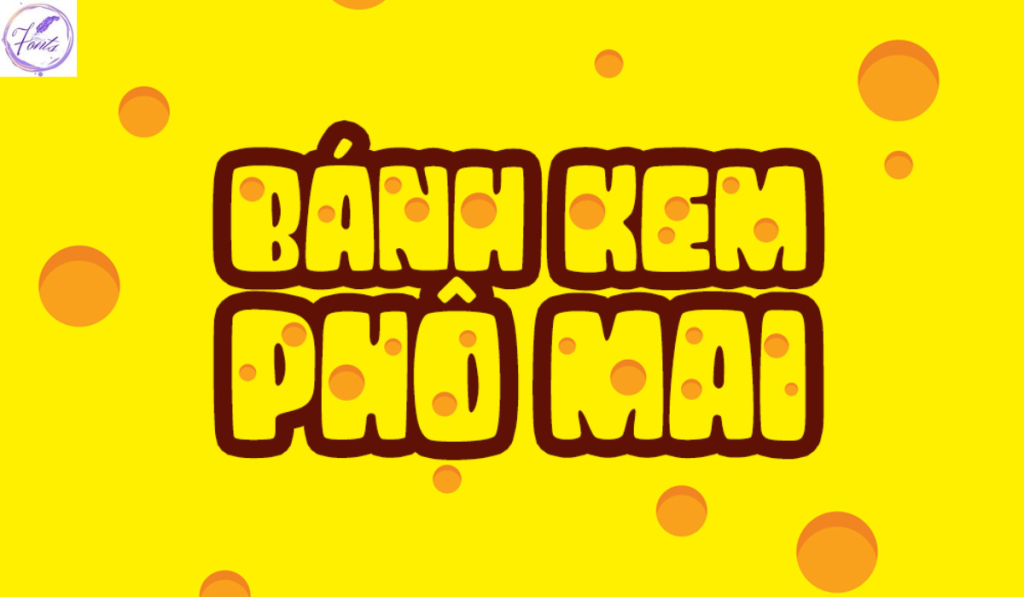
Đắm chìm vào thế giới của sự sáng tạo và niềm vui với font chữ hoạt hình việt hóa – một trong những phông chữ được yêu thích nhất trong cộng đồng thiết kế đồ họa. Với hơn 100 kiểu chữ độc đáo và đầy màu sắc, font chữ hoạt hình mang đến một làn gió mới mẻ, tràn đầy năng lượng cho mọi dự án thiết kế của bạn. Dù bạn đang tìm kiếm một phông chữ cho truyện tranh, game hay bất kỳ tác phẩm sáng tạo nào, font chữ hoạt hình việt hóa sẽ là lựa chọn tuyệt vời để thể hiện cá tính và sự độc đáo.
Font chữ hoạt hình việt hóa ngộ nghĩnh – Font TH Jelly Bomb
Font TH Jelly Bomb là một trong những font chữ hoạt hình việt hóa ngộ nghĩnh, mang đến sự vui tươi và đáng yêu cho các thiết kế. Với các nét chữ bo tròn, font này rất phù hợp cho các sản phẩm dành cho trẻ em và các ấn phẩm vui nhộn. Font được phát hành vào năm 2024, mang đến sự mới mẻ cho người dùng trong lĩnh vực thiết kế đồ họa.
Font chữ hoạt hình TH Gyoza
Font chữ hoạt hình TH Gyoza là một lựa chọn thú vị cho các thiết kế vui nhộn và dễ thương. Với các nét chữ mềm mại và hình dáng độc đáo, font này rất phù hợp cho các sản phẩm dành cho trẻ em và các ấn phẩm sáng tạo. Font được phát hành vào năm 2024, mang đến sự mới mẻ cho người dùng trong lĩnh vực thiết kế đồ họa.
Font chữ hoạt hình nét tròn TH Motley Forces
Font chữ hoạt hình nét tròn TH Motley Forces là một kiểu chữ độc đáo, mang đến sự vui tươi và sáng tạo cho thiết kế. Với đường nét mềm mại và phong cách vui nhộn, font này rất thích hợp cho các sản phẩm dành cho trẻ em. Font được phát hành miễn phí và có thể sử dụng trong các dự án thương mại.
Font chữ hoạt hình Fz Cat Comic
Font chữ hoạt hình Fz Cat Comic là một lựa chọn tuyệt vời cho các thiết kế vui nhộn và sáng tạo. Với kiểu dáng độc đáo, font này mang lại cảm giác trẻ trung, năng động, rất phù hợp cho các sản phẩm truyền thông và truyện tranh. Font được phát hành vào năm 2022, cung cấp đầy đủ các ký tự tiếng Việt để người dùng dễ dàng sáng tạo nội dung.
Font chữ hoạt hình serif có chân – Font Goligan
Font Goligan là một kiểu chữ serif có chân, mang đậm phong cách hoạt hình, thích hợp cho các thiết kế vui nhộn và sáng tạo. Font này được phát hành vào ngày 7 tháng 1 năm 2024, với các đặc điểm nổi bật như độ dày phông chữ đa dạng và các đường nét mềm mại, tạo cảm giác thân thiện. Goligan là lựa chọn lý tưởng cho các dự án đồ họa và truyền thông.
Font chữ hoạt hình nét mềm mại – Cornetta Font
Cornetta Font là một font chữ hoạt hình nét mềm mại, mang phong cách đáng yêu và hiện đại. Font chữ này sẽ mang đến một chút niềm vui cho thiết kế của bạn với các ký tự hỗ trợ đa ngôn ngữ và các dấu câu tiêu chuẩn. Cornetta Font bao gồm hai phiên bản: nét mảnh và nét thường, giúp tăng tính linh hoạt cho các tác phẩm của bạn.
Font hoạt hình Estrella
Estrella Font là một kiểu chữ hiển thị với những đường cong biểu cảm, mang lại cảm giác vui tươi và năng động. Được thiết kế bởi Uncarving Nation, font này được phát hành vào ngày 4 tháng 4 năm 2023, lấy cảm hứng từ các kiểu chữ thập niên 70 với những nét chấm phá psychedelic. Estrella rất phù hợp cho các dự án thương hiệu, áp phích và tiêu đề.
Font chữ hoạt hình độc đáo ngộ nghĩnh – Oogie Boogie Font
Oogie Boogie Font là một font chữ hoạt hình độc đáo và ngộ nghĩnh, được thiết kế bởi Gaut Fonts. Font này thuộc thể loại Fancy > Cartoon, mang đến vẻ ngoài vui tươi, phù hợp cho các dự án sáng tạo. Oogie Boogie Font được phát hành miễn phí cho mục đích cá nhân và đã thu hút được 390,463 lượt tải về.
Font hoạt hình SVN Cheeseburga
SVN Cheeseburga là một font chữ phong cách hoạt hình dễ thương, được thiết kế để mang lại cảm giác vui tươi và sinh động cho các dự án đồ họa. Font này được phát hành vào ngày 5 tháng 5 năm 2021, với các đặc điểm nổi bật như đường nét mềm mại và hình khối độc đáo, phù hợp cho các sản phẩm sáng tạo và trẻ em.
New Cheese Font
New Cheese Font là bộ font chữ mới, sáng tạo và độc đáo, phù hợp cho các thiết kế hiện đại, trẻ trung. Font có nhiều phong cách khác nhau, từ cổ điển đến hiện đại, mang lại sự linh hoạt và sáng tạo cho các dự án thiết kế.